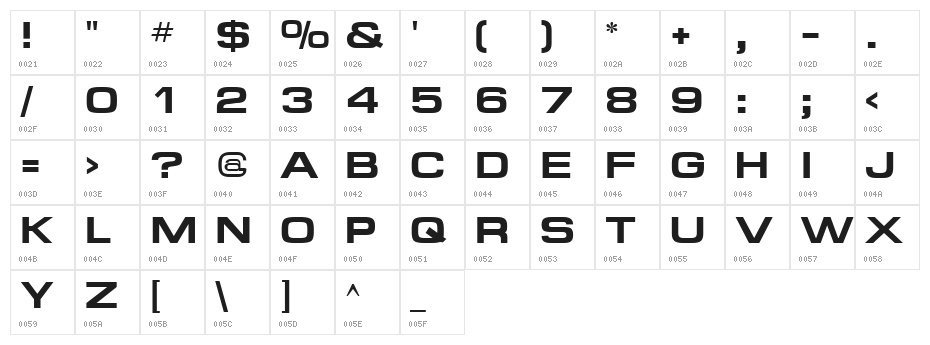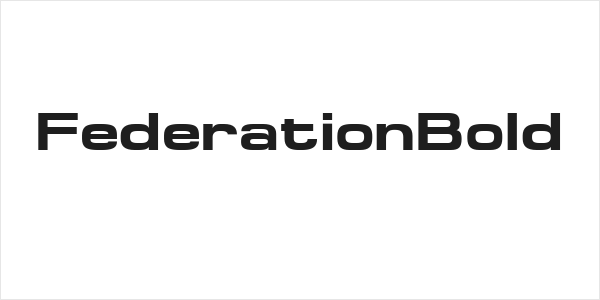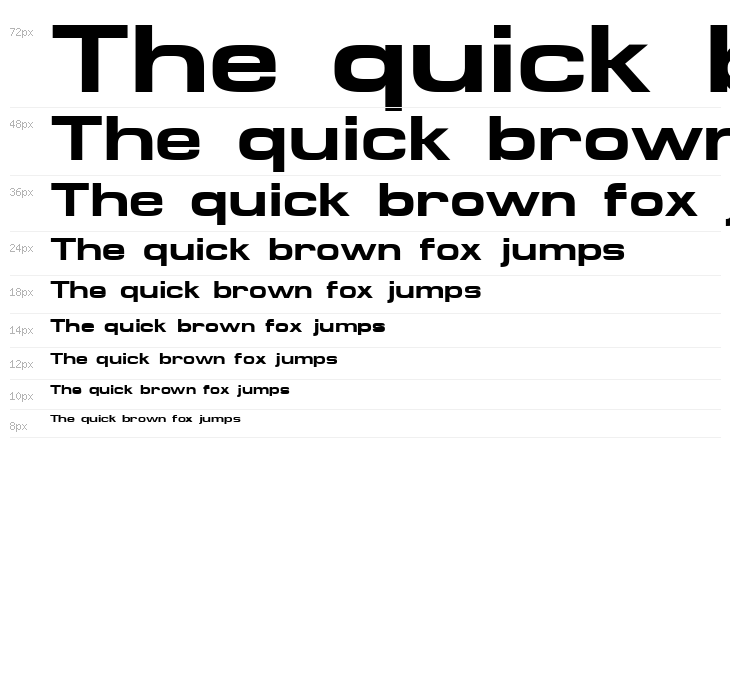
FederationBold Font
| Anwendungsfall | Headlines, Logos, Branding |
| Vorgeschlagene Projekte | Ideal for branding, headlines, posters, and digital media where a strong, modern presence is desired. |